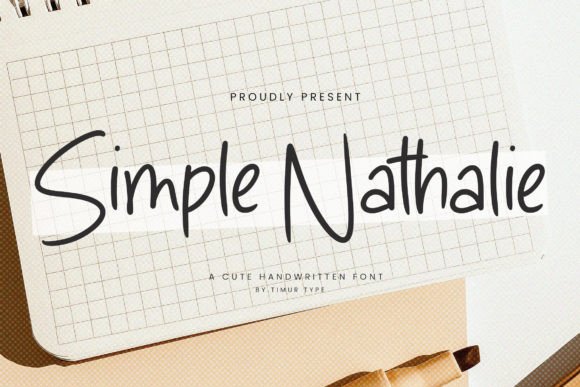
Simple Nathalie
適切なデザイン要素を見つけるのは難しい場合がありますが、Simple Nathalieは作品を即座に引き立てる優れたコレクションを提供します。
POD(オンデマンド印刷)製品、結婚式の招待状、またはソーシャルメディアのグラフィックを作成している場合でも、Simple Nathalieは理想的です。